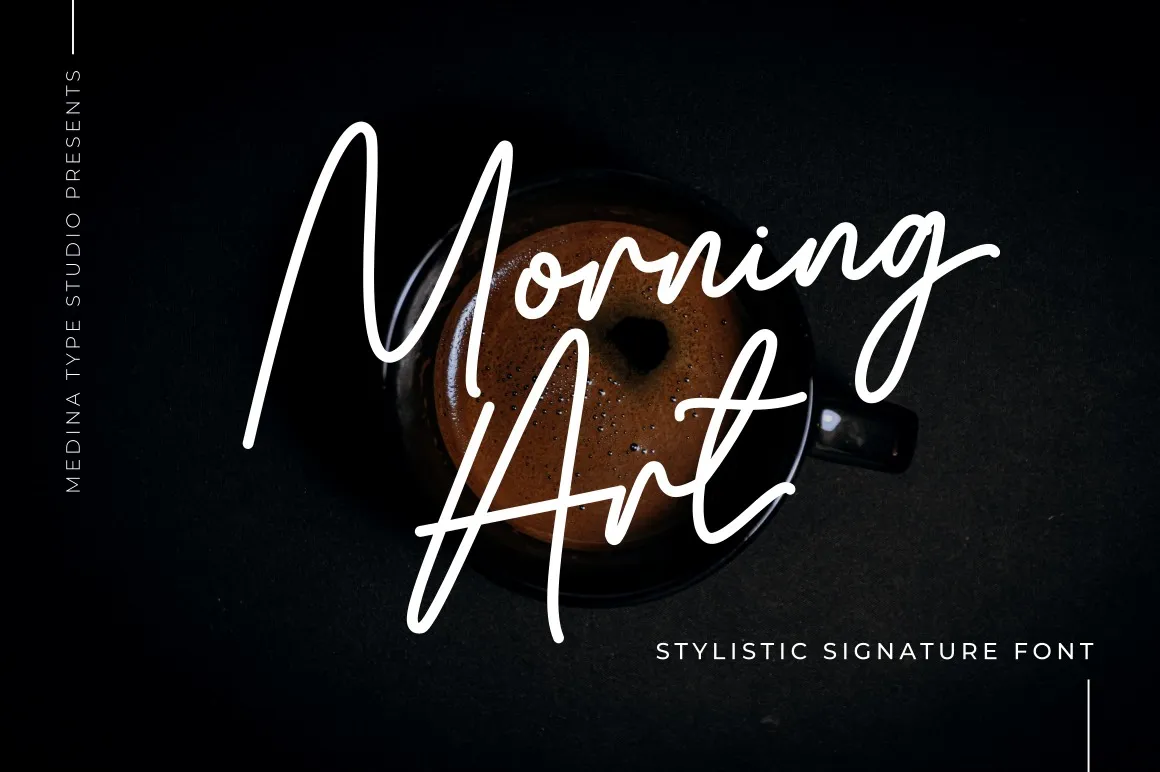
Morning Art Font – Download Grátis
Essa fonte ‘Morning Art Font’ é perfeita para projetos que precisam de uma nota pessoal, seja ela uma cartinha íntima ou um projeto de escrita elegante. Ela foi criada com um estilo script e linha única, inspirada em uma caligrafia realista que flui suavemente. Os resultados são incrivelmente exquisitos, românticos e elegantes. É perfeito para qualquer trabalho que precise de um toque pessoal ou emotivo. Esta font é PUA codificada, o que significa que você pode acessar todas as linhas de gílios e desenhos alternativos facilmente. O ‘Morning Art Font’ do designer 99designs não apenas oferece beleza e elegância, mas também uma maneira sofisticada de personalizar textos em suas criações de arte. É perfeito para designers de gráficos que buscam adicionar um toque único e romântico a seus projetos.